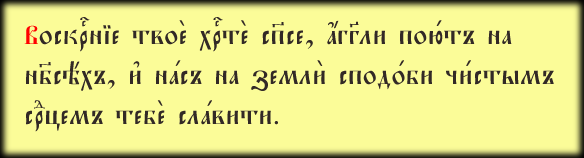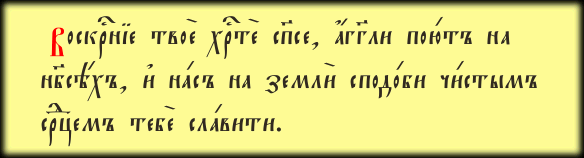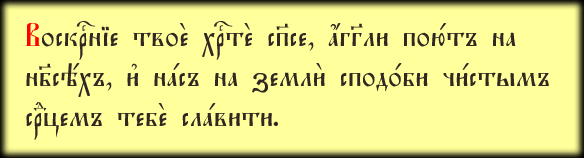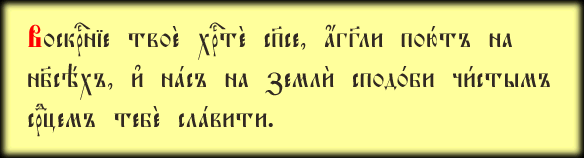
Гарнитура использовалась в синодальных изданиях второй половины 19 - начала 20 века. Размер (кегль) оригинальных литер довольно большой: высота строчных букв порядка 5 мм. Этой гарнитурой набирались напрестольные Евангелия, крупноформатные издания акафистов и т.п.
Автор шрифта -- Константин Спекторов. Шрифт воспроизводит буквицы из зимней (1642 г.) и летней (1643 г.) частей Пролога. Буквицы данного типа широко использовались в изданиях Московского печатного двора в XVII в.
Шрифт предполагается использовать только для буквиц. Этим обусловлены некоторые ограничения в составе букв и знаков. Буквы имеются все, кроме "ука лигатурного", Ъ, Ы, Ь. Из надстрочников присутствуют только оксия, звательцо и исо. Знаки препинания отсутствуют.
Гарнитура от SoftUnion ((C) 1994 SoftUnion Ltd. Created by A. Shishkin and N. Vsesvetskii).
Шрифт от Ленполиграфмаша ((С) AO Lenpoligraphmash, 1994).
В отличие от Irmologion, шрифт "Ирмос" действительно повторяет гарнитуру из изданий Синодальной типографии начала 20 в. (например, "Ирмологий" 1913 года).
Гарнитура для буквиц. Буквы имеются все, даже те, что в виде буквиц не встречаются. Контуры достаточно сложные, что может напрягать растеризаторы.
Шрифт сделан на основе гарнитуры из изданий Синодальной типографии начала 20 века. Название взято от книги, из которой она перерисовывалась: "Ирмологий" издания 1913 года.
Довольно распространенная заголовочная гарнитура из дореволюционных изданий 18 - 20 вв.
Имеется довольно известный коммерческий шрифт Psaltyr, воспроизведенный с тех же печатных образцов, что и Kathisma. Отличий немного: буквы Kathisma чуть шире, но межбуквенные расстояния -- меньше; некоторые буквы нарисованы иначе; тщателнее проработан кернинг.
Основная, наиболее распространенная заголовочная гарнитура из дореволюционных изданий. В печатных оригиналах встречается много вариантов этой гарнитуры, отличающихся друг от друга мелкими деталями. Шрифт Oglavie повторяет один из них.
Из современных коммерческих шрифтов Oglavie больше всего похож на Slavjanic, но прорисован более качественно и отличается от него большей компактностью и контрастом.
Комплект шрифтов Orthodox (© 2002 Андрущенко Н. А. Спасо-Преображенский Соловецкий ставропигиальный мужской монастырь)
Шрифты разработаны в соответствии с требованиями проекта стандарта
Единой церковно-славянской кодировки 8-битных шрифтов UCS8
(Unified Church Slavonic Standard).
Гарнитура взята из изданий второй половины 16 века (типографии городов Вильно и Острога). Создателем гарнитуры, предположительно, является Петр Мстиславец, восточнославянский типограф, соратник первопечатника Ивана Фёдорова.
Оригинальная гарнитура применялась в богослужебных книгах прошлого века, издаваемых типографией Почаевской Лавры. За основу Pochaevsk Ucs была взята достаточно точная ее цифровая версия Pochaevsk. В разных вариантах шрифтов встречаются указания на разных дизайнеров: Orthodox Information Data Associates (год неизвестен); Starin, Russian Antiquities, developed by Nikita Simmons (1996); Archbishop John (1999).
Еще один декоративный, подходящий для оформления заголовков шрифт. Похож на Zlatoust, но с засечками и "узелками".
Дизайнером исходного цифрового шрифта является Никита Всесветский ((С) SoftUnion Ltd., 1994. Created by N.Vsesvetskii). Шрифт имеет свой аналог в дореволюционных изданиях. Правда, автор цифровой версии несколько изменил пропорции букв (по отношению к исходной печатной гарнитуре буквы в шрифте вытянуты по вертикали процентов на 20-30) и, наоборот, вытеснил вверх и сжал надстрочники (в исходном шрифте надстрочные знаки чувствуют себя более свободно). Без учета этих двух моментов, а также некоторых небольших упрощений рисунка букв, цифровой шрифт представляет собой достаточно точную копию исходного дореволюционного.
Шрифт подходит для оформления различного рода заголовков.
Елизаветинские шрифты — это шрифты, содержащие символы старой русской
орфографии (т. е. орфографии, действовавшей в России до 1918 года),
а также символ ударения.